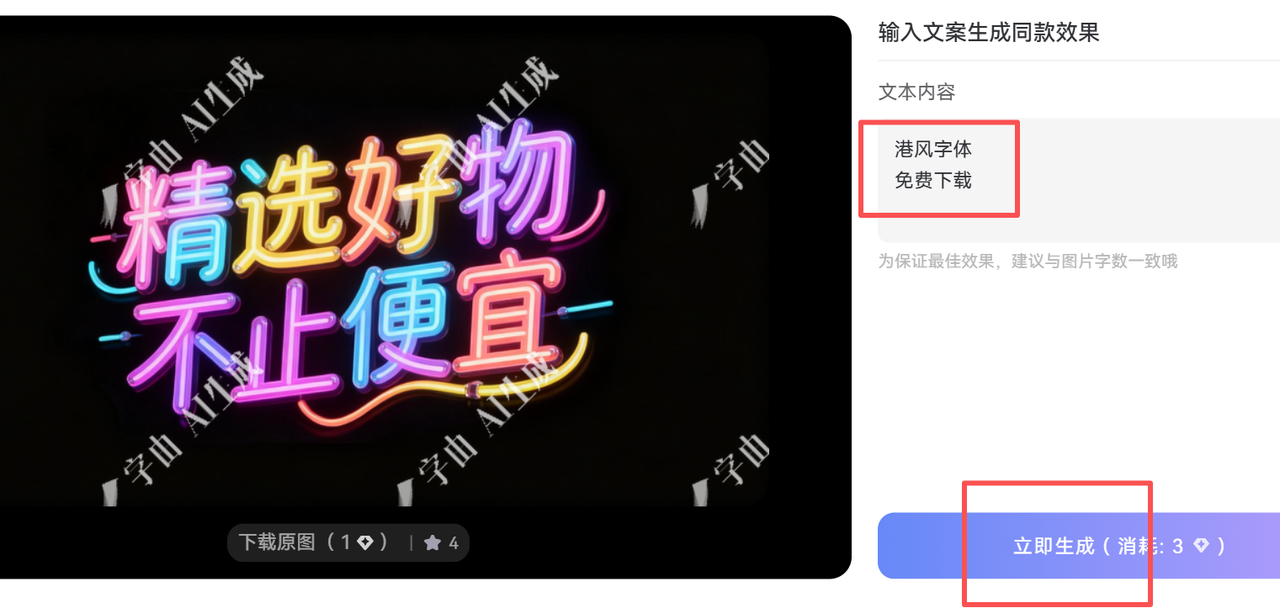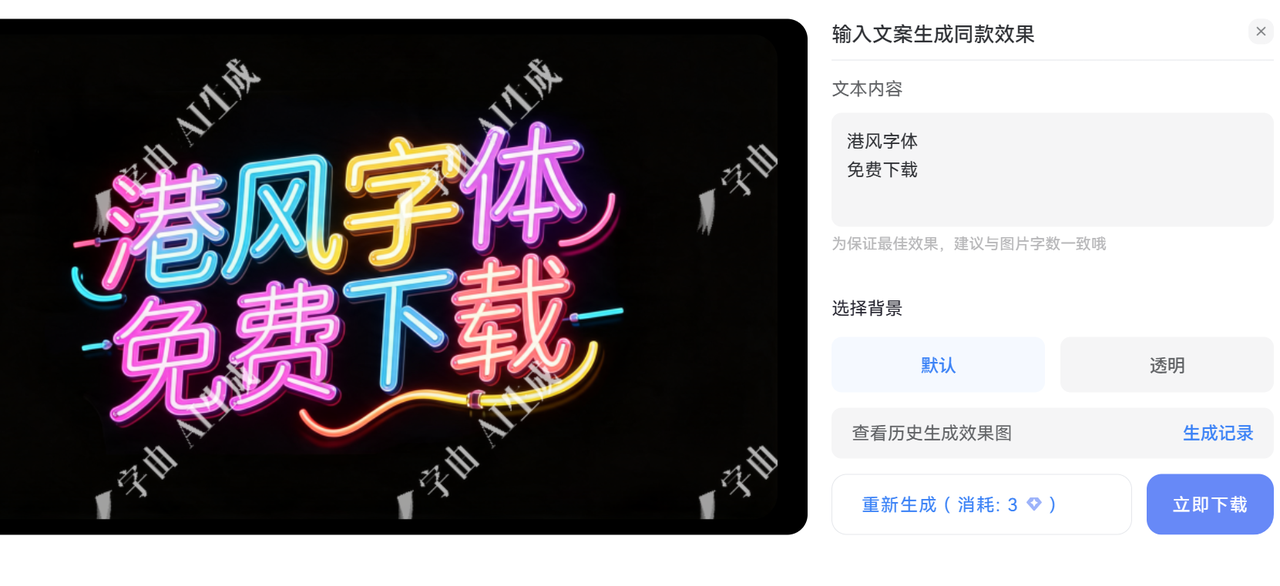
港风字体免费下载指南,如何用 AI 轻松搞定港风字体
你在做设计的时候,是不是也常为了寻找那种“老电影感”的港风字体而头疼?想要那种自带霓虹灯光、或是像八九十年代手写招牌的韵味,结果在网上搜了一圈,很难找到符合的港风字体。
今天我想和大家分享一个我最近常用的方法——利用字由的 AI 字体生成工具。通过这个工具,你可以直接在线生成符合港风气质的文字,再也不用担心版权问题,而且效果非常惊艳。
字由 AI 港风字体生成教程
打开字由AI生成字体页面,在搜索框中搜索“港风”
在得到的港风字体模板列表中,选择自己喜欢的模板,输入自己的文字,点击一键生成即可。
等待几十秒后,就可以查看同款港风字体的效果了,点击立即下载,就可以免费把字体下载到本地使用了
我第一次打开 字由 AI 字体生成页面 时,最直观的感受就是“简单”。它不需要你懂复杂的图形设计软件,甚至不需要你有排版经验。
1. 极致简单的操作体验
打开页面后,你可以按照字体风格进行筛选,或者直接搜索关键词,就能获得多个字体模板,选择模板后,在输入框输入文字,点击立即生成即可,整个过程非常简单,几分钟就能搞定。
1. 不用下载字体包
很多时候,我们需要的仅仅是几个字的标题。下载一套完整的字体安装包,利用 AI 生成,我们可以把精力集中在设计效果本身,而不是处理冗余的字体文件。
以前我们需要花费大量时间在找字体、试字体、确认版权上,现在有了这种在线生成方式,我可以把 80% 的时间花在创意本身。
如果你也是正在寻找“港风字体”的设计爱好者,或者是一个想给自己的设计、作品集增加一点独特风格的普通用户,建议你一定要亲自试一下这个平台。它不需要你成为一名专业的设计师,也能帮你把脑子里的那种“复古氛围”变成现实。